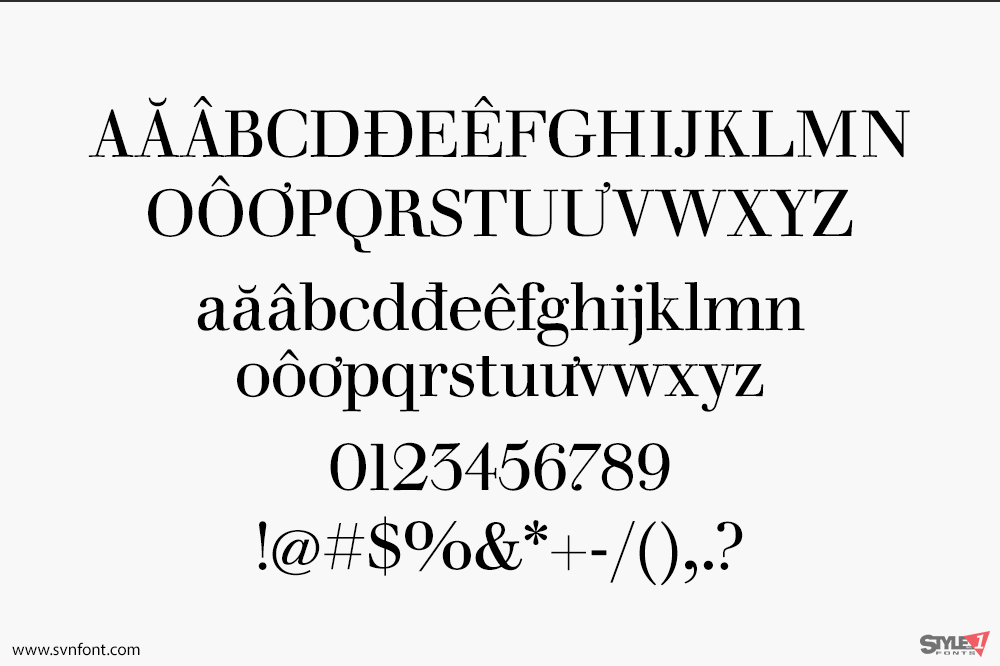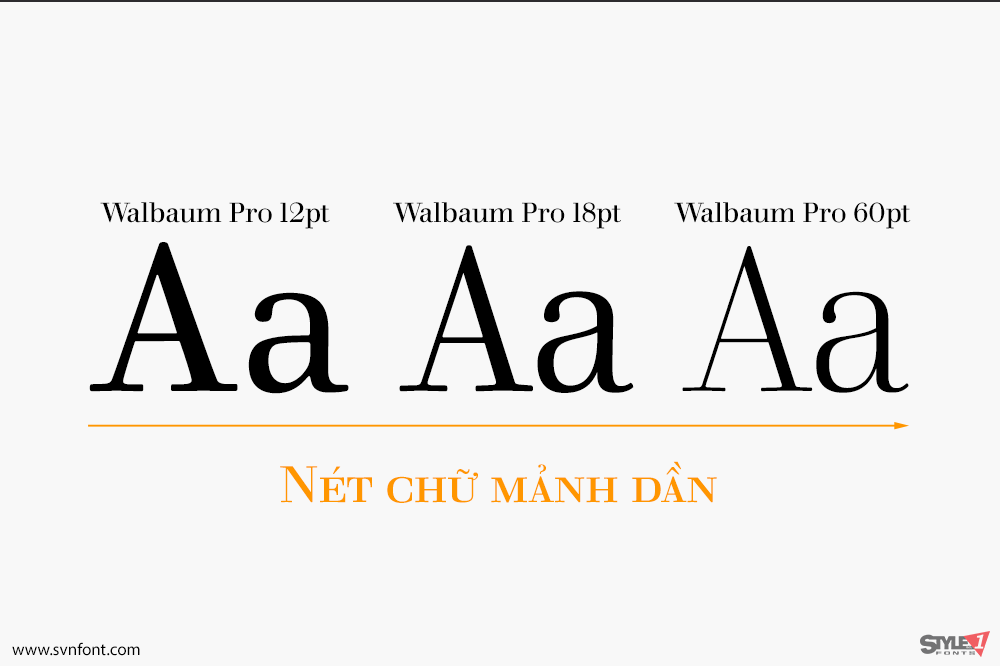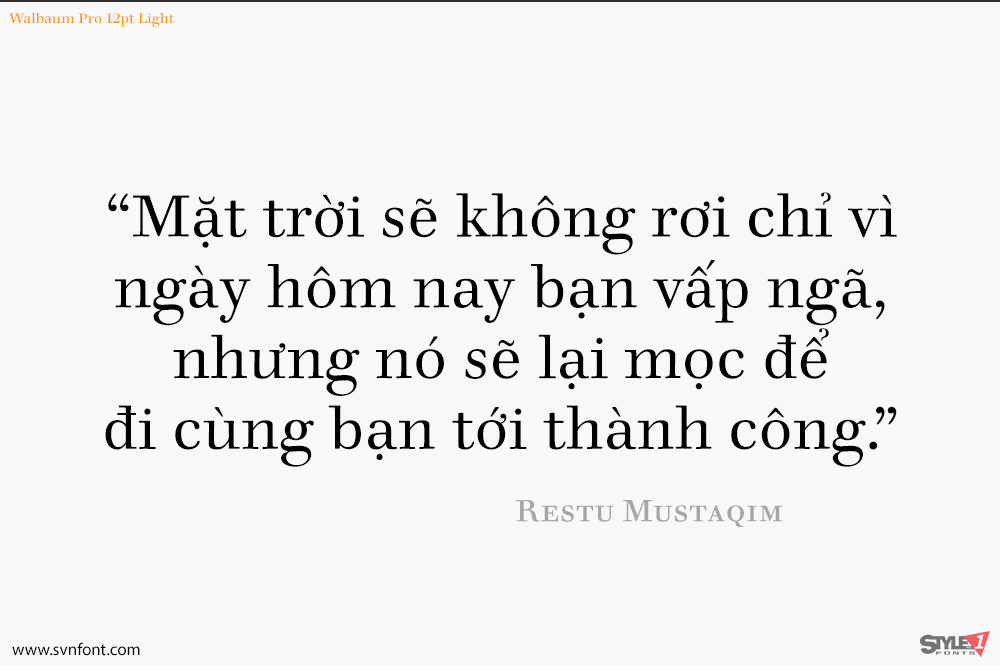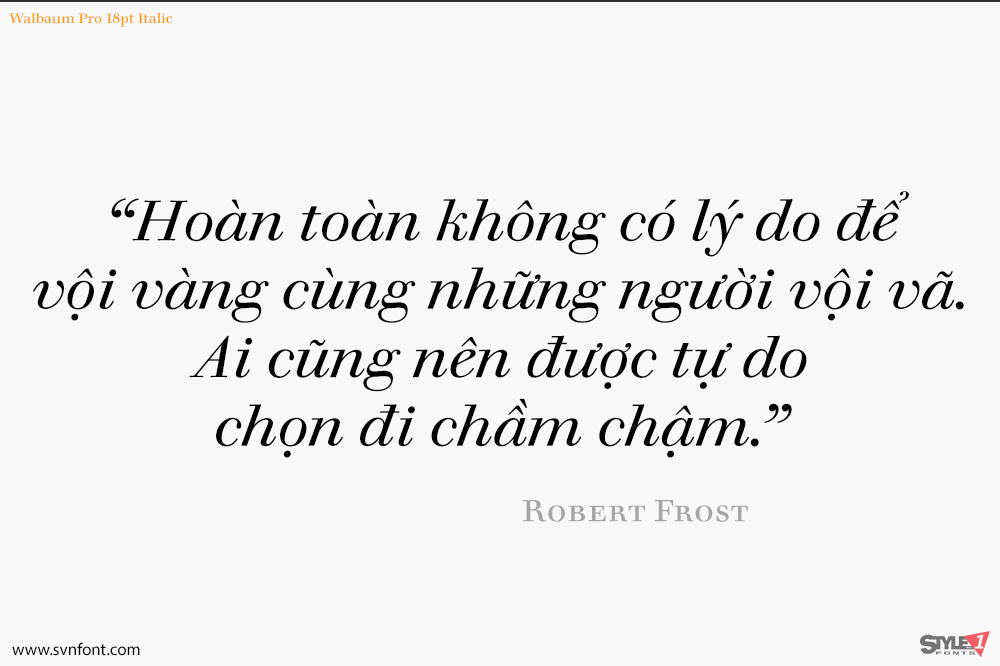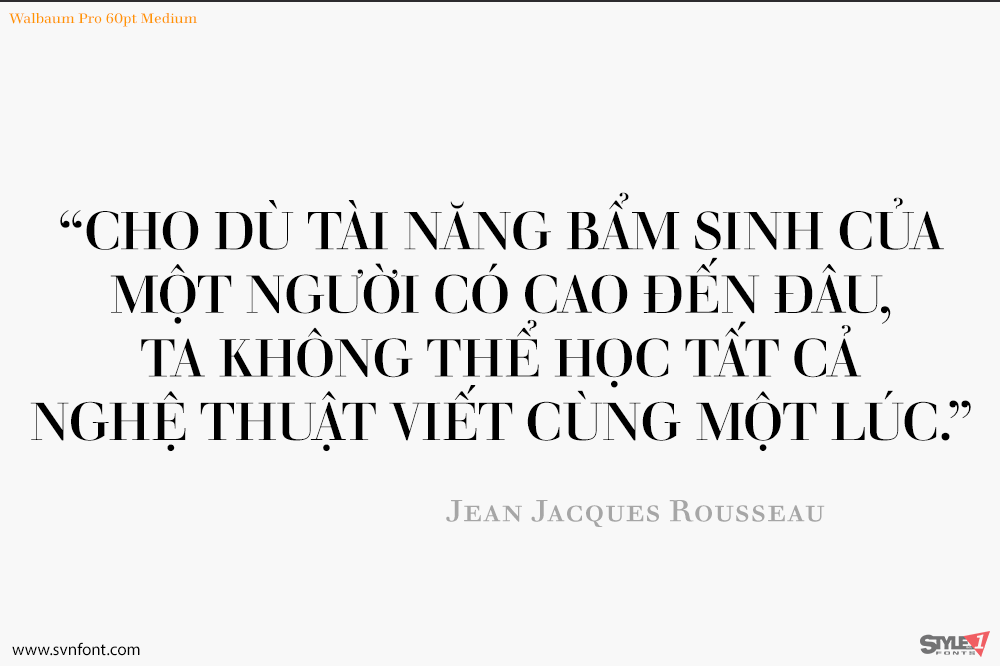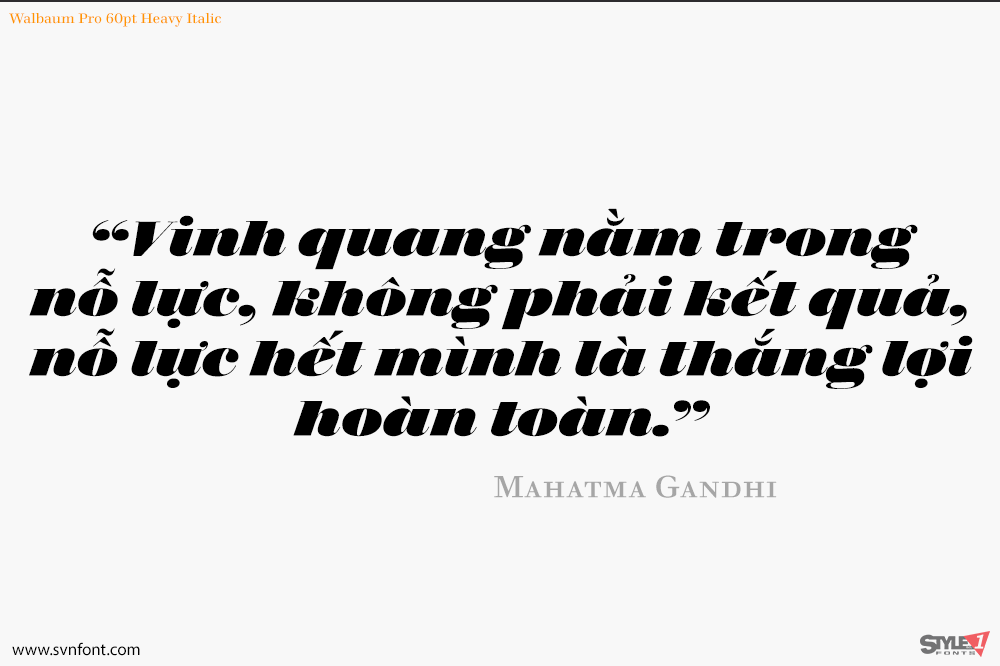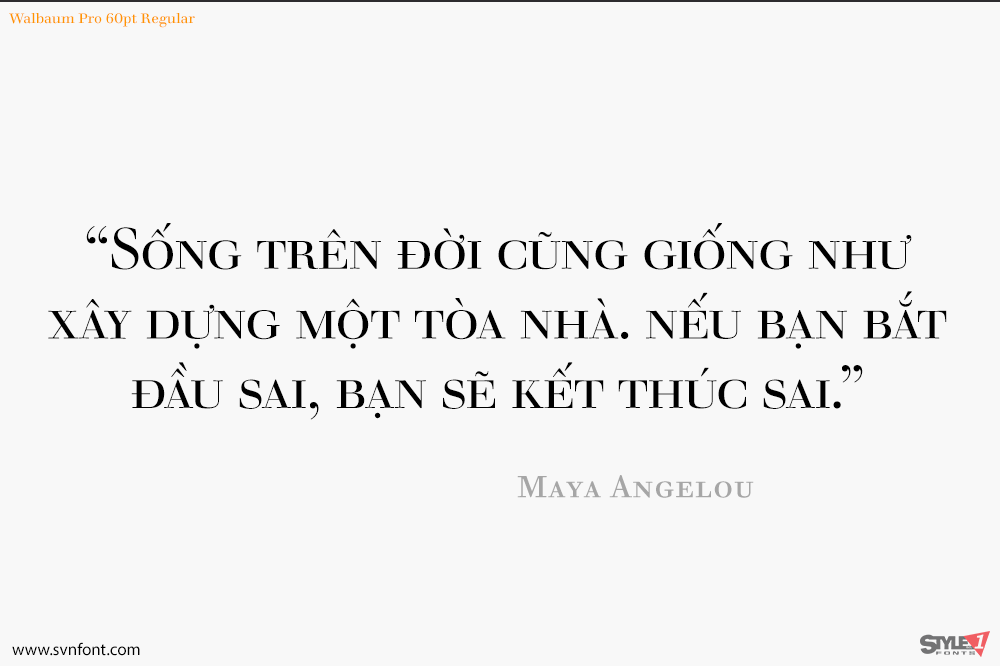
Được thiết kế lần đầu vào đầu những năm 1800, Walbaum chưa bao giờ đạt được sự công nhận và lượng khán giả mà nó xứng đáng có được – bất chấp vẻ thanh lịch và tinh tế. Bộ phông chữ mở rộng này đã được khôi phục hoàn toàn, bao gồm 32 độ đậm cùng với các ký tự trang trí và hai nét cắt trang trí.
Walbaum mang đến sự ấm áp mà các phông chữ tương đương như Bodoni hay Didot còn thiếu, tạo cảm giác dễ tiếp cận và dễ đọc một cách tự nhiên. Đội ngũ Monotype gồm Carl Crossgrove, Charles Nix và Juan Villanueva đã tuân thủ ý định ban đầu của nhà thiết kế Justus Erich Walbaum, đồng thời kết hợp tác phẩm của con trai ông vào một số độ đậm hiển thị cực đoan hơn – mở rộng khả năng của Walbaum mà không làm mất đi tinh thần của nó. Các độ đậm văn bản hoạt động tốt cho các yêu cầu của môi trường kỹ thuật số, trong khi các độ đậm trang trí và hiển thị mang đến các hình thức điêu khắc, ấn tượng hơn. Một điểm bất thường là bộ phông này cũng bao gồm một loạt các ký tự trang trí phong phú. Từ những biển quảng cáo khổng lồ đến các văn bản siêu nhỏ trên máy đọc sách điện tử, Walbaum đều đáp ứng được.
Bộ phông chữ này có sẵn ở định dạng phông chữ OpenType OTF và bao gồm hơn 600 ký tự với các tính năng OpenType như chữ in hoa nhỏ, số kiểu cũ và số dạng hàng, số tỷ lệ và số dạng bảng, phân số và chữ ghép.
Nhà thiết kế: Carl Crossgrove, Charles Nix, Juan Villanueva
Nhà phát hành: Monotype